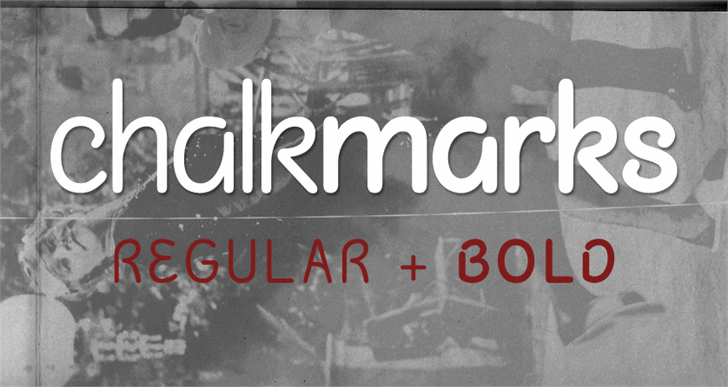
A Chalk Marks é uma elegante fonte sem serif que transmite um sentimento quase cíntico, embora não seja realmente escrita à mão. Esta é uma representação básica – para a versão completa da fonte e para uma licença comercial, visite: https://creativemarket.com/justlikethistrain/335308-Chalk-Marks. Hamilton, o designer desta fonte moderna com influências cínticas, tem criado um ícone do novo século para aqueles que valorizam a simplicidade e a frescura na tipografia. Chamada simples ou complicada, a Chalk Marks é uma escolha ideal tanto para títulos quanto para textos de corpo. Suas linhas fluidas e delicadas criam um toque cálido, quase carinhoso ao seu texto, tornando-a perfeita para aplicações que buscam um ar descontraído ou moderno sem perder o poder persuasivo da tipografia sem serif. A Chalk Marks é uma fonte perfeitamente adaptada tanto para aplicativos digitais quanto impressos, e sua design única a faz se destacar em qualquer plataforma de apresentação gráfica.